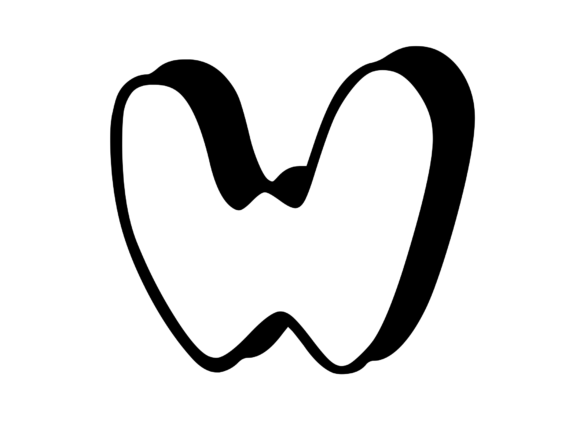
Friendly Shaded Comic Hand Drawn Mono W
Việc tìm kiếm các thành phần thiết kế phù hợp có thể là một thách thức, nhưng Friendly Shaded Comic Hand Drawn Mono W cung cấp một bộ sưu tập đặc biệt giúp nâng tầm công việc của bạn ngay lập tức.